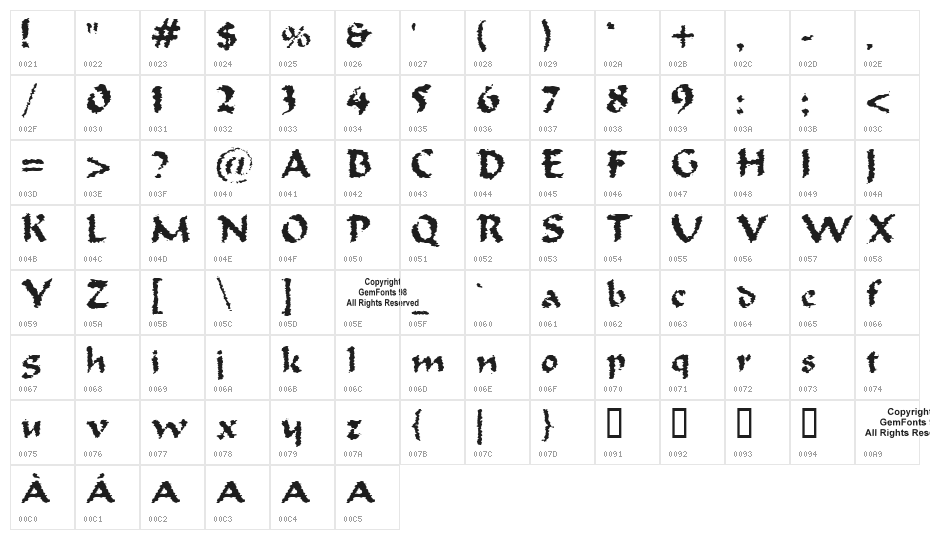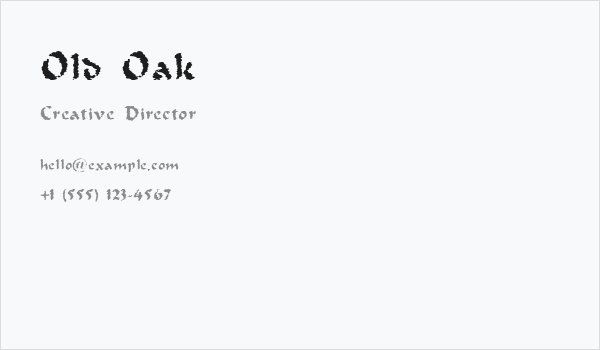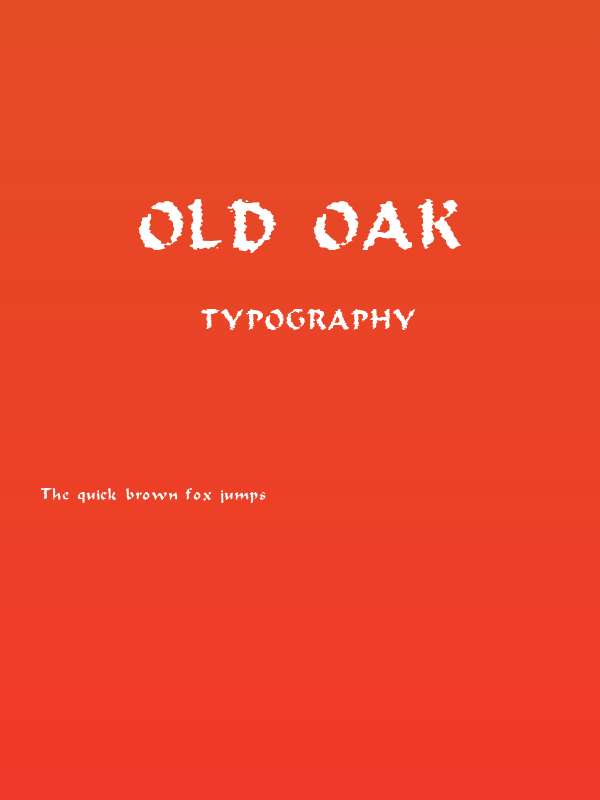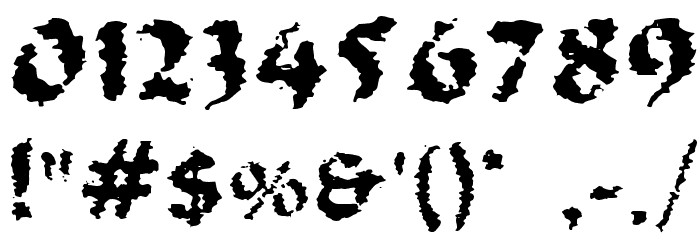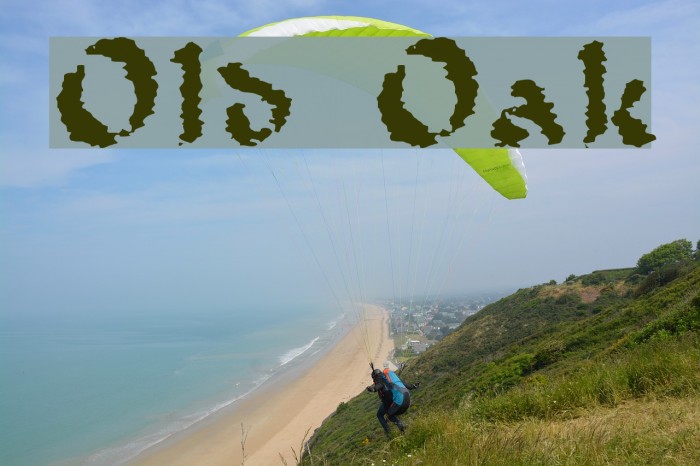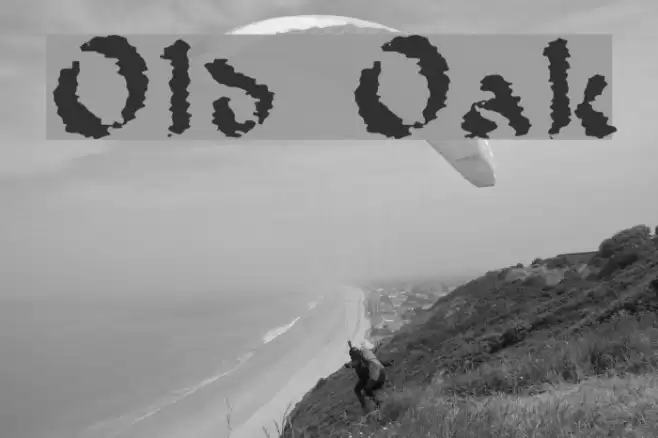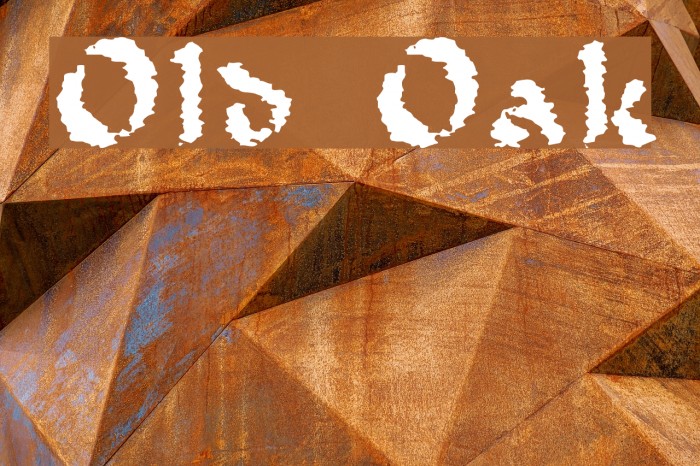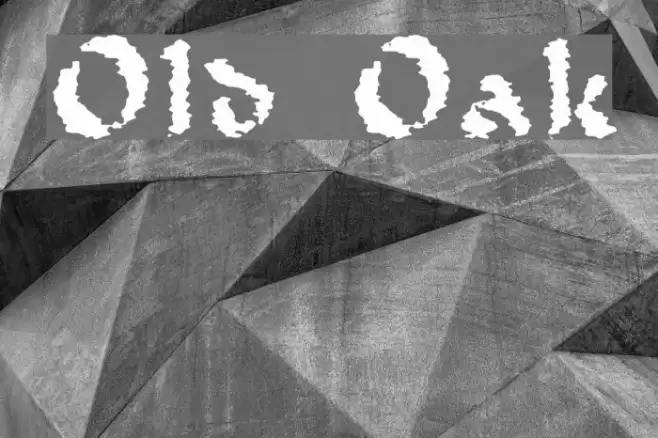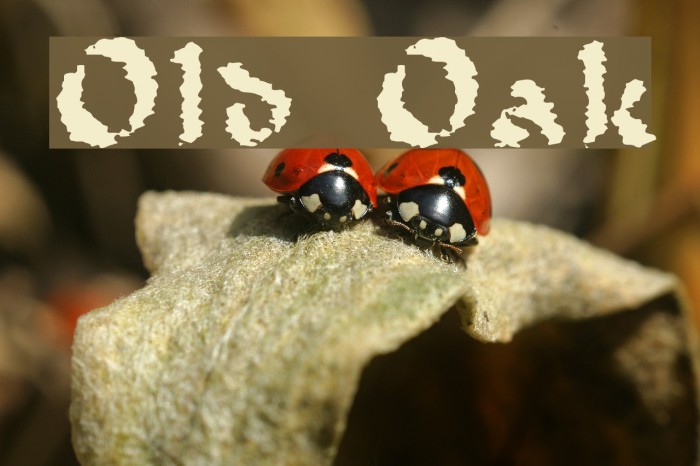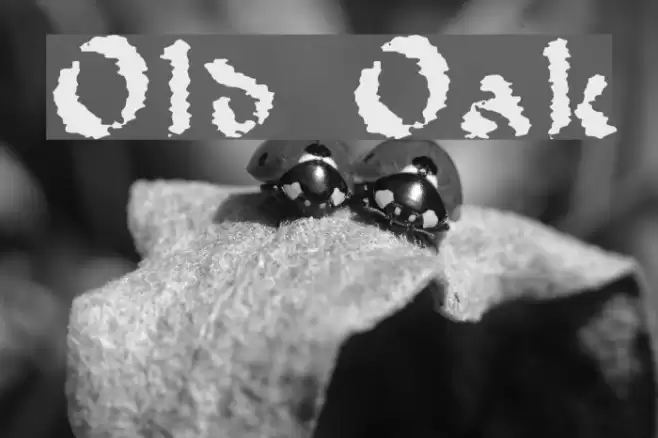
Old Oak Font
| Categorías | Script |
| Estilo general | Vintage |
| Caso de uso | Logos, Headlines, Posters |
| Proyectos propuestos | Ideal for branding, packaging, posters, and signage that require a rustic or vintage touch. |